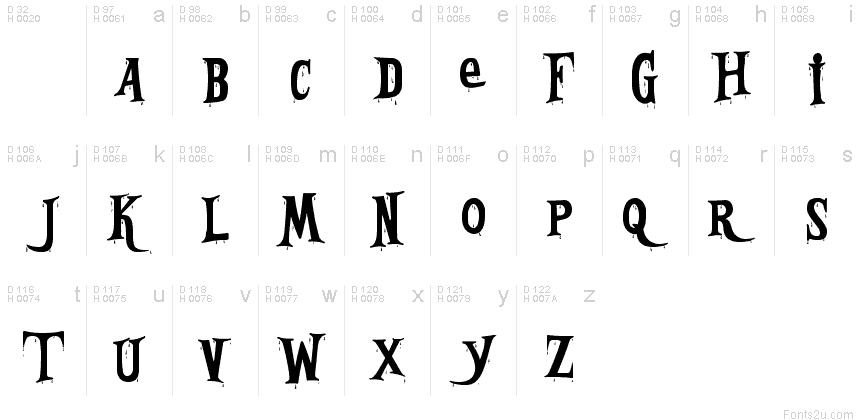
A fonte Bleeding Freaks, criada por Thomas W.Otto da Norfok Inc., é uma tipografia display assustadora e gratuita que transpira o drama dos filmes de terror. Traços pretos e espessos retorcem-se em formas deformadas, enquanto gotas de tinta parecem escorrer das letras, como se tivessem acabado de sair de uma cena de crime. O espaçamento é apertado e claustrofóbico, fazendo com que as palavras se aglomerem numa massa ameaçadora e irregular que estabelece imediatamente um tom arrepiante.
Com a Bleeding Freaks, pode elevar os seus cartazes de Halloween, sinalização de casas assombradas, títulos de filmes de terror, logótipos de jogos, miniaturas de YouTube e convites para festas de arrepiar ao nível dos clássicos de culto. Esta fonte gratuita destaca-se quando usada em tamanho grande e em negrito. Combine-a com uma sem serifa simples no texto principal para manter a legibilidade, deixando que os títulos gritem por si.